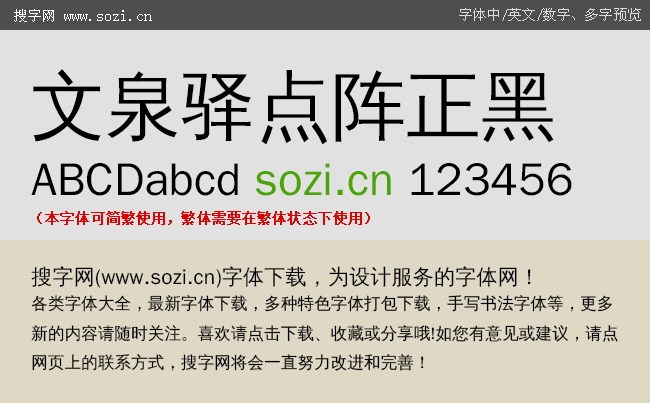
文泉驛點(diǎn)陣正黑
搜字網(wǎng)提供一款文泉驛點(diǎn)陣正黑中文字體下載,文泉驛點(diǎn)陣正黑是一種支持大字符集的開源字體,文泉驛正黑包含了所有常用簡(jiǎn)體中文、繁體中文所需要的漢字,為非襯線字體,筆畫對(duì)比度明顯,清晰銳利,易于閱讀。可用于報(bào)刊雜志排版,也適用于平面廣告,圖書印刷等廣告設(shè)計(jì)場(chǎng)合使用。